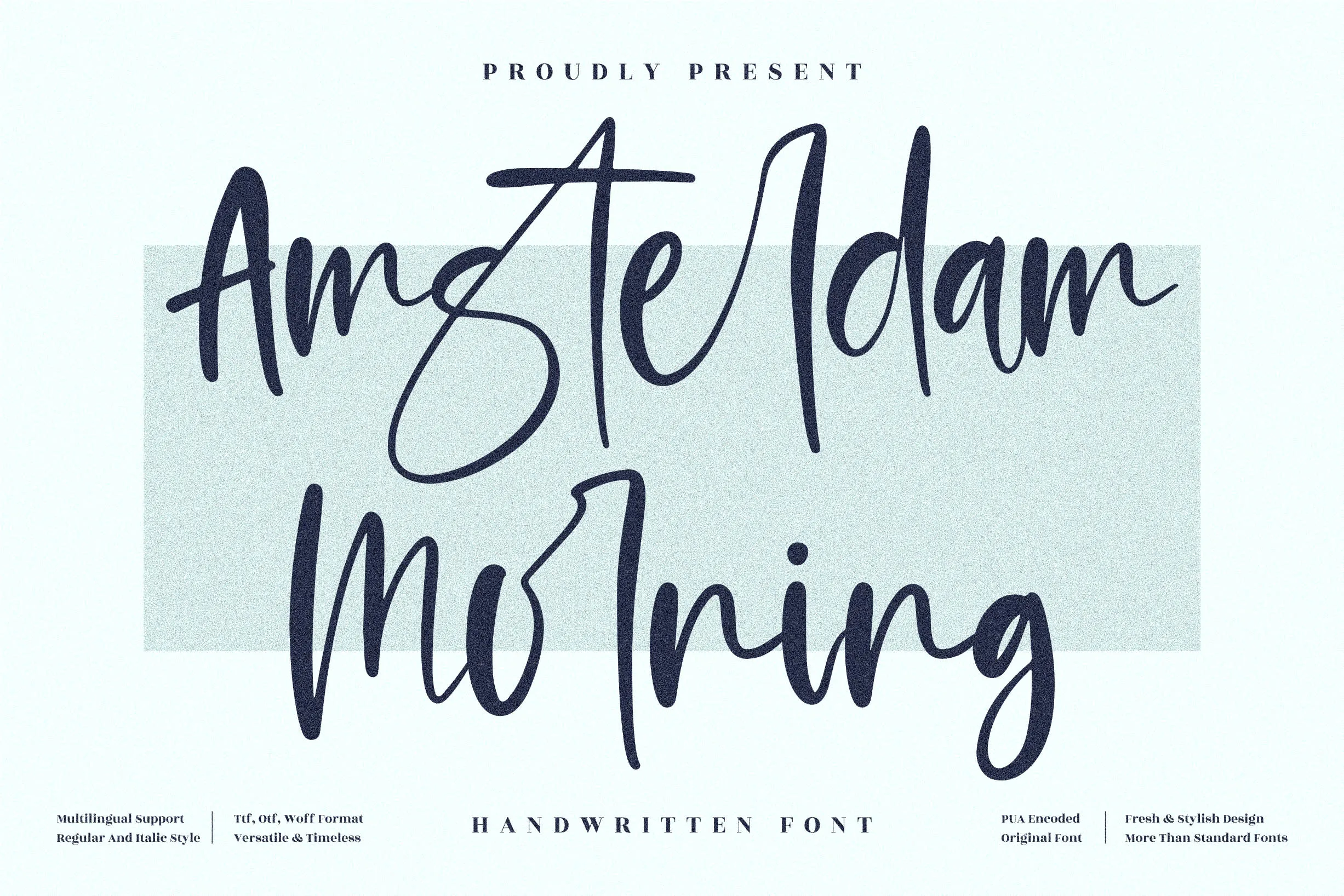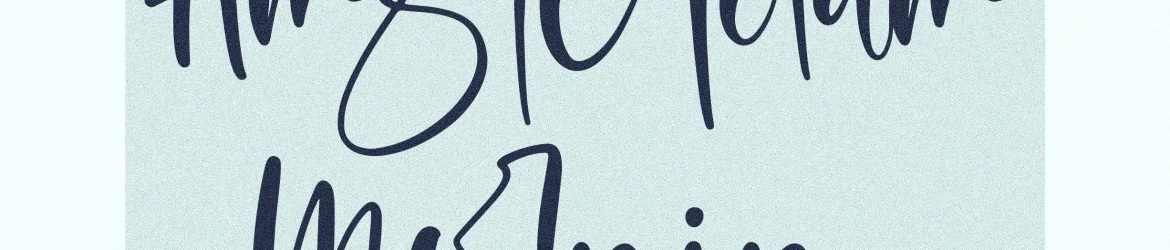
Amsterdam Morning Font – Download Grátis
A Amsterdam Morning Font é uma elegante fonte escrita a mão ideal para projetos que buscam um toque único e refinado. Perfeita tanto para criações artesanais como para projetos de luxo, essa fonte suavemente se adapta a diversos gêneros de design, desde identidades visuais até artefatos quotidianos. Seja ela o texto de uma etiqueta gourmet ou o desenho de um mala personalizada, Amsterdam Morning atua como um complemento perfeito para qualquer projeto que exija um toque delicado e autoral. Suave e acolhedora, a Amsterdam Morning Font é uma escolha ideal para quem deseja dar ao seu design um toque sofisticado, em harmonia com o estilo de vida brasileiro. Não importa qual seja seu próximo projeto; essa fonte escrita a mão certamente irá tornar sua criação única e singular.